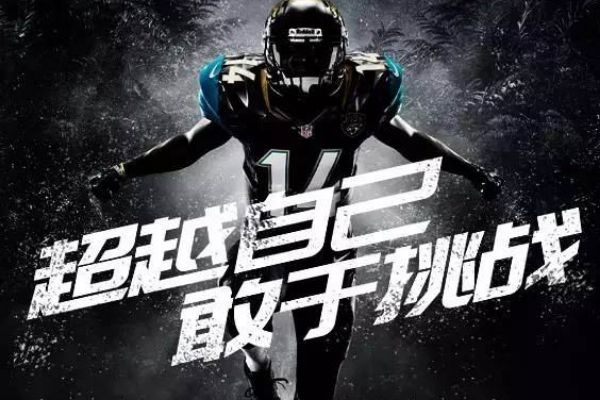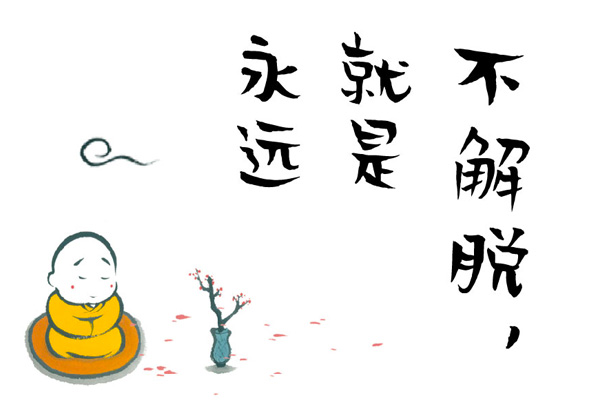
哪里有免费商用的复古字体?盘点3个设计师必看的字体下载平台
你是不是也经常遇到这样的尴尬?在设计海报、制作视频封面或者排版公众号文章时,脑海里明明想的是那种带有怀旧感、高级感的“复古风”,却在字库里翻来覆去只找到几款平庸的黑体和宋体。本文分享 4 个可以获取免费商用的复古字体。
1. 常见免费商用复古字体推荐
1. 庞门正道标题体
这款字体非常扎实,有一种八九十年代电影海报的厚重感。如果你的设计需要突出的标题,用它准没错。它在视觉上非常有张力,既有复古的工业气息,又不失现代设计的简洁感。
1. 站酷快乐体
虽然名字叫“快乐体”,但它那种圆润、俏皮的风格,很容易让人联想到上世纪七八十年代的卡通插画或复古手绘招牌。用在一些需要传递亲和力、轻复古氛围的设计里,效果出奇地好。
1. 贤二体
这款字体带有明显的手写质感,笔触之间有种质朴的温度。在做一些文学类、民俗类或者自然感强的复古设计时,这款字体能带来非常独特的人文气息,让人觉得非常亲切。